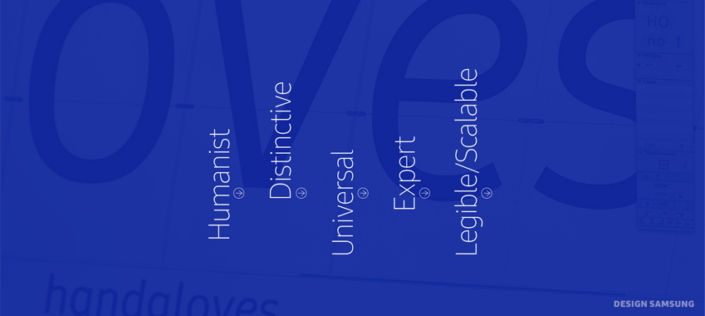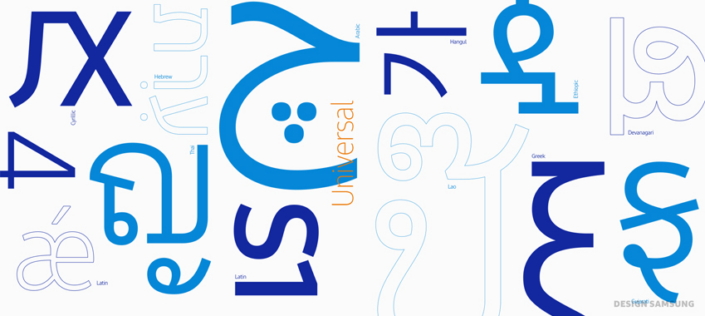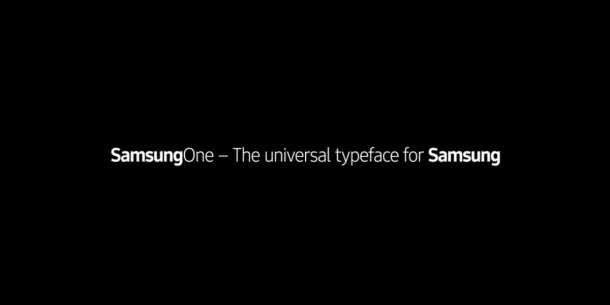
SamsungOne ฟ้อนต์ใหม่ที่ทาง Samsung เตรียมใช้ในทุกๆอุปกรณ์ของบริษัท
จากที่ก่อนหน้านี้คงเคยเห็นกันไปแล้วว่า Apple และ Google ได้พัฒนาฟ้อนต์ของตัวเองออกมาใช้งาน ล่าสุดวันนี้ทาง Samsung ก็ได้ออกมาประกาศแล้วครับว่าทางบริษัทจะมีการพัฒนาฟ้อนต์ของตัวเองที่ใช้ชื่อวัน SamsungOne โดยเจ้าฟ้อนต์ดังกล่าวนี้จะนำไปใช้กับทุกๆอุปกรณ์ของ Samsung ไม่ว่าจะเป็นสมาร์ทโฟน, TV, ไมโครเวฟ หรือแม้กระทั่งเครื่องซักผ้า ซึ่งแน่นอนครับว่ามันจะเป็นฟ้อนต์ที่แสดงถึงตัวตนของ Samsung ในแบบที่ว่าใครเห็นฟ้อนต์ดังกล่าวจะต้องร้อง..อ๋อ Samsung ประมาณนั้นเลยครับ
โดยในการออกแบบ SamsungOne นั้น ทางบริษัทได้จับมือร่วมกับนักออกแบบฟ้อนต์ชื่อดังนาย Neville Brody ซึ่งการออกแบบดังกล่าวจะทำออกมาให้สามารถครอบคลุมกว่า 400 ภาษา และกว่า 25,000 สัญลักษณ์บนโลกใบนี้ จะบอกว่าเป็นงานช้างก็คงจะไม่ผิดนักครับ
ทั้งนี้ทาง Samsung ยังวางเป้าหมายของ SamsungOne ไว้ว่าจะต้องออกแบบมาให้ดู Humanist (มีความเป็นมนุษย์) ด้วยรูปแบบตัวอักษรและองศาการเขียนที่มีความลื่นไหล อีกทั้งยังจะต้องมีความโดดเด่นเป็นเอกลักษณ์บ่งบอกความเป็นตัวเองได้ดี และแน่นอนว่าฟ้อนต์ SamsungOne จะต้องสามารถใช้ได้แบบสากลและดูมีความเป็นมืออาชีพ ซึ่งทั้งหมดทั้งมวลนี้ยังต้องอยู่บนพื้นฐานที่สามารถทำให้ทุกคนสามารถอ่านเข้าใจได้ง่าย แม้ว่าตัวอักษรที่นำมาใช้จะมีขนาดเล็กหรือใหญ่ก็ตาม
สำหรับการเปิดตัวของ SamsungOne นั้นตอนนี้ทางบริษัทยังไม่ได้ข้อมูลใดๆออกมา ซึ่งหากมีข้อมูลเพิ่มเติมออกมาทางเราจะรีบมาอัพเดทให้กับเพื่อนๆโดยเร็วที่สุดครับ